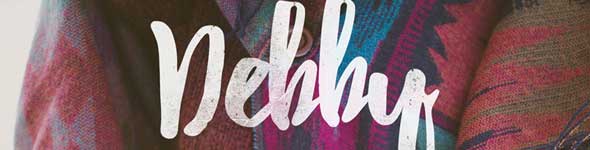
Webデザイナーのためのハイクオリティ無料フォント集 商用も可能なフォントを合わせて30種類!
最高品質のフリーフォントは欲しくありませんか?もちろん欲しいですよね!では、このリストに収録した素晴らしい、高品質のフリーフォントをチェックしてみることをお勧めします。
無料で手に入ることが信じられないほど高品質なフリーフォントを30種類集めました。印刷でもデジタル作品でも、皆さんのデザインに組み合わせることができます!
これらの高品質なフリーフォントを使えば、ロゴ、ウェブサイト、広告、チラシなどのプロジェクトを格好良く作成できます。
太字と細字、サンセリフとセリフ、大文字と小文字などさまざまなスタイルがあります。このリストの中からお気に入りがきっと見つかるはずです。
BIG JOHN / SLIM JOE
これはすばらしいフリーフォントです! Behanceのプレゼンテーションも素晴らしいです!アイソメトリック、シャドー、3Dなど多くのエフェクトをかけて、このフォントを使用できます。
DEBBY
Debbyは、手描きのフォントであり、ブラシテクスチャを備えています。これは皆さんのプロジェクトをよりパーソナルに、そしてある意味不完全にするために特別にデザインされました。皆さんは結婚式の招待状、標語ポスター、ロゴなどあらゆるものに使用できます。
BARON
Baron(Neue)は、古典的なサンセリフフォントファミリに触発された大文字の表示書体で、ポスターあるいはロゴタイプ、見出しなどのあらゆる種類のクリエイティブなプロジェクトに組み合わせることができます。
ANDERS
現代のフォントデザインからの影響力を利用して、このデザイナーは本当に最小限で少しユニークなものを求めていました。沢山のスケッチと多くの作業の結果、こんな素晴らしいものを完成しました。
ADAM.CG PRO
これはFuturaにインスパイアされた大文字のサンセリフフォントです。シャープで無駄のないデザインは、見出し、ポスター、タイトル、キャプションに適しています。皆さんののフォントコレクションに加えておくべきフォントであることは間違いありません。
GAGALIN
Gagalinはコミックの書体からインスピレーションを受けてデザインされていて、間違いなく皆さんのフリーフォントコレクションに加える価値があるフォントです。このフォントは格好よくて、クリエイティブであり、それはコミック風のデザインにぴったりです。
BASTON
自分のフォントコレクションに加えるための、本当に素敵なフォントをお探しなら、このBastonをチェックしてみてください。このフォントは、商用でも個人用途でも自由に使うことができます!ヴィンテージ感のある古い見た目をしていて、様々な作品に使用することができます。
AVENTURA
この格好の良い、高品質のフリーフォントは、キャンプとトラベルをイメージして作られました!皆さんのクリエイティブなプロジェクトで映える「アウトドア感」と素敵な細かい装飾を備えています!
ALCUBIERRE
Alcubierreはジオメトリック・サンセリフフォントです。これは最小限のデザインを施された無駄のないフォントで、色々な用途に使用できます。 Alcubierreは、商用、個人用途を問わず自由に使用できます。
ATHENE
Atheneは外見の優雅さを保つことにも役立っているモダンでジオメトリックなスマートさを持つセリフフォントです。個人、商用に拘わらず自由に使用できます。
ACCENT
Accentは、短い単語やタイトル用に設計された商業、個人両用の、実験的なフリーのディスプレイフォントです。実にモダンでユニークなデザインです。
AQUA GROTESQUE
これは美しい1940年代風の書体です。ポスターやロゴなど、さまざまな作品制作に使用でき、完全にフリーです!
HANDLETTER
手書き風フォントをお探しでしたら、これがベストでしょう。これは無料で使えるとても格好の良いレタリングフォントです!プリントとデジタルデザインの両方で、思う存分活用しましょう!
MANIFESTO
この格好の良い、スリムな大文字フォントは、イタリアの合理主義運動に影響を受けています。現代的で魅力的なデザインのおかげで、ヘッダー、Webデザインプロジェクトなど、多くのクリエイティブなプロジェクトに適しています。
NICKAINLEY
Nickainleyは皆さんのコレクションに追加する価値のあるフォントです。それは大文字、小文字、数字、句読点を含む伝統的でヴィンテージなデザインのモノラインの手書きフォントです。
MAXWELL
MAXWELLは、ウェブ、プリント、モーショングラフィックスなどあらゆるプロジェクトに役立ちます。見出しやロゴ、あるいはワードマークに最適です。
SLOT
SLOTは、半円形パターンの丸文字フォントです。Slotは、個人用、商用の両方で完全にフリーで使えます。このフォントをチェックして、ダウンロードし、皆さんのプロジェクトで試しに使ってみてください!
BREAK
Breakは、無料で使用できる最新のフォントファミリです。太字、極細、大文字、小文字、そして数字と記号の5つのスタイルを備えています。
BUKHARI SCRIPT
Bukhari Scriptは、Webや印刷、ロゴ、ポスター、バッジ、サイネージ、名刺、Tシャツデザインなど、さまざまなデザインプロジェクトにうまく取り入れることができるユニークなデザインの太字モノラインの筆記体風フォントです。
SIMPLIFICA
SIMPLIFICAは、一様で細い線が特徴の、やや縦長のサンセリフフォントです。
ARCTIC
Arcticは現代的なスラブセリフフォントです。その無骨な北部地域の雰囲気を醸し出している、力強い線で構成されています。
GLAMOR
Glamour Type Familyには、1につき200以上の文字を備える、24種類のフォントの驚くべきセットが含まれています。このフォントファミリーは、皆さんの作品をより魅力的なものにします。個人、商用を問わず自由に使用できます。
CORNERSTONE
Cornerstoneは無駄のないモジュラーフォントで、無料で利用できます!ヘッダーに使った時に映える、モダンで長方形のフォントデザインです!
HIGH TIDE
High Tideは、タイトル、見出し、ポスター、ロゴなどのためにデザインされた、大文字の装飾的なフォントです
PARKER
Parkerは手作り・ヴィンテージ感のあるフォントです。ヴィンテージ風デザイン、Tシャツ、ロゴ、ポスターなどに最適です。このフォントは個人用途の範囲で自由に使用できます。
RECKONER
「Reckoner」は、商用、個人用を問わず自由に使用できます。 Reckonerには現在2つの線の太さがあります。
NOOA
このフォントは、伝統的なセリフとサンセリフの絶妙な組み合わせです。プレビュー写真のような現代的な使い方が最適です。
JAAPOKKI
Jaapokkiは、2つのバリエーションと沢山の絵文字を備えたフリーフォントです。このフォントは、デザイナーのフリーフォントコレクションにとって非常に価値があります。
MELMA
このフォントは、ロゴ、バッジ、結婚式招待状、Tシャツ、レターヘッド、看板、ラベル、ニュース、ポスター、バッジなどのさまざまな目的に使用できます。
CABANA
これはAdrien Coquetによる手作りの新しいフリーフォントです。 素敵な装飾が施されていて、皆さんのプロジェクトに取り入れれば間違いなく素晴らしいものが完成するでしょう!